싸인은 단순한 서명이 아니라, 자신을 대표하는 중요한 요소예요. 따라서 자연스럽고 멋진 싸인을 만들기 위해서는 꾸준한 연습이 필수적이에요. ✍️
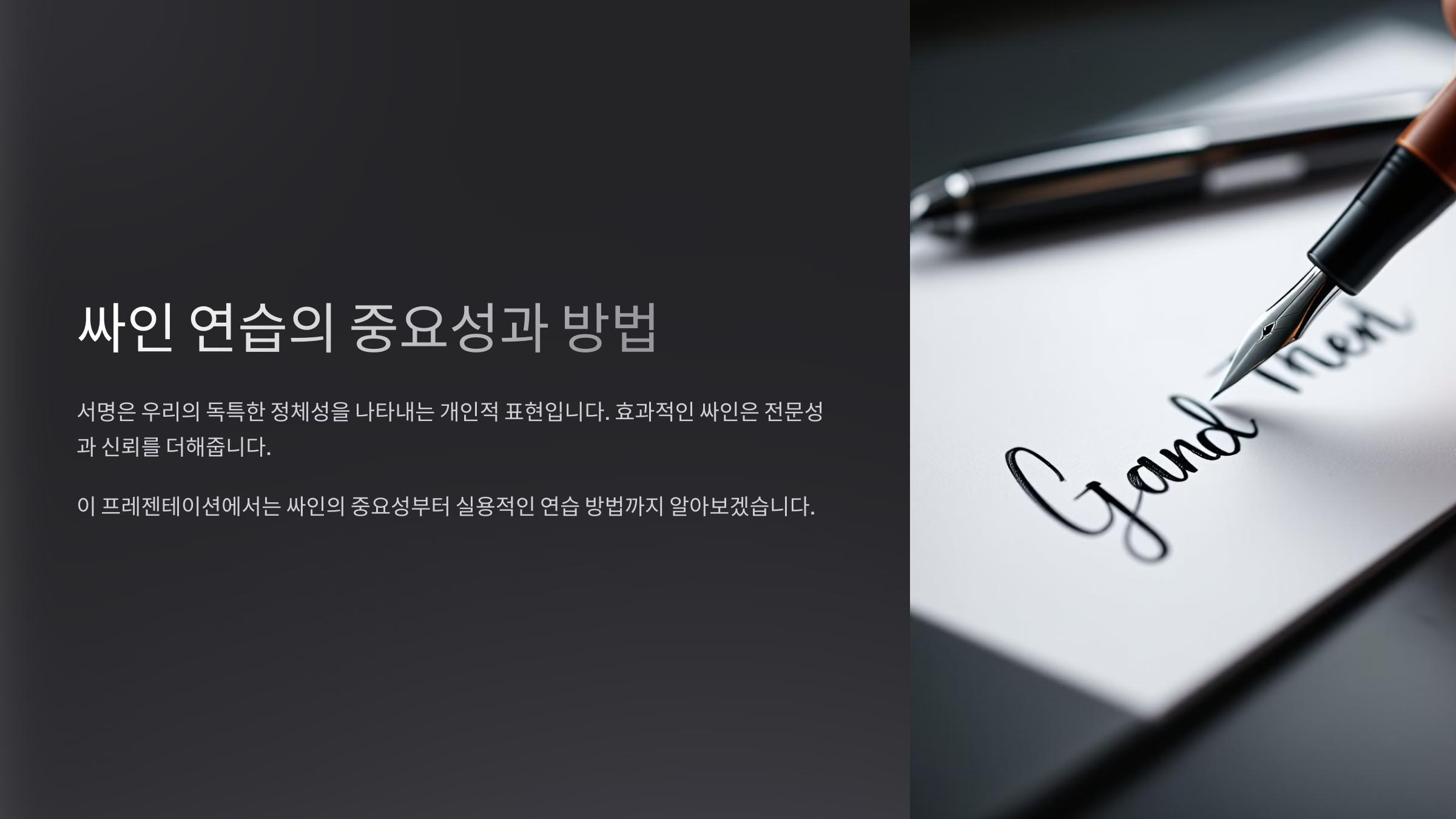
싸인을 연습하는 과정이 어렵게 느껴질 수도 있지만, 올바른 방법을 따르면 빠르게 손에 익힐 수 있어요. 그렇다면, 싸인 연습이 왜 중요한 지부터 살펴볼까요? 🔍
싸인 연습이 중요한 이유 ✍️
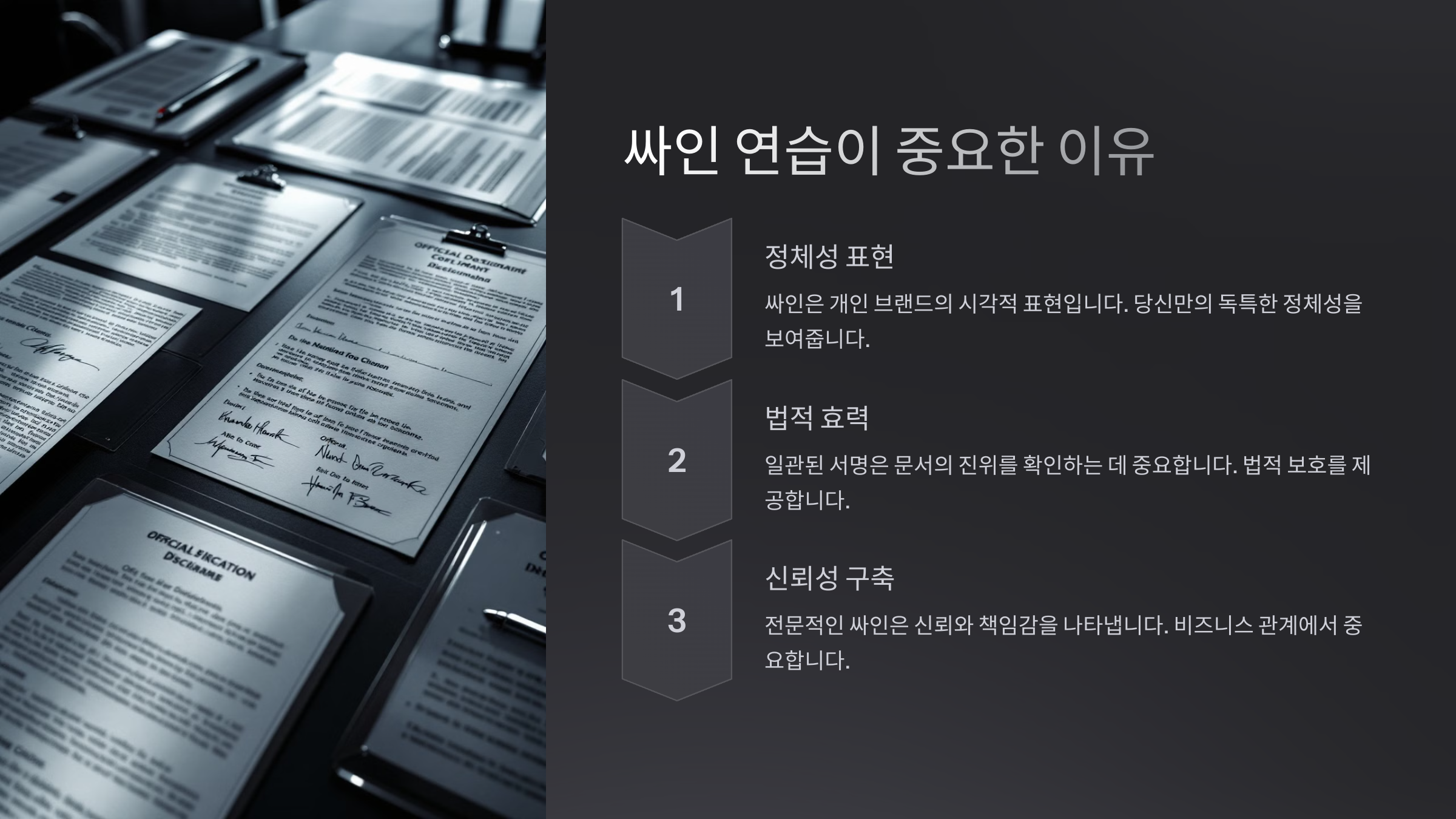
싸인은 단순한 이름이 아니라 자신을 나타내는 하나의 상징이에요. 공식 문서, 계약서, 예술 작품, 심지어 팬 사인회까지 다양한 상황에서 사용되죠. 🖋️따라서 멋진 싸인을 만들려면 반복적인 연습을 통해 손에 익혀야 해요. 연습을 꾸준히 하면, 싸인이 자연스럽게 나올 뿐만 아니라 가독성, 속도, 스타일을 동시에 잡을 수 있어요! 🚀
📌 싸인 연습이 필요한 4가지 이유 ✅
이유 설명 가독성 향상 연습을 하면 글자가 더욱 정돈되고 또렷해짐 속도 개선 손에 익으면 빠르고 자연스럽게 싸인을 할 수 있음 스타일 완성 꾸준한 연습을 통해 자신만의 독창적인 싸인 형성 자신감 상승 싸인할 때마다 당당하고 프로페셔널한 인상을 줄 수 있음 싸인 연습을 하면 자신감이 생기고, 어디서든 멋진 싸인을 남길 수 있어요! 그렇다면, 싸인 연습을 시작하기 전에 어떤 도구가 필요한지 알아볼까요? 🖊️
싸인 연습에 필요한 도구 🖊️
싸인 연습을 시작하기 전에 적절한 도구를 준비하는 것이 중요해요. 좋은 도구를 사용하면 싸인의 스타일을 더 쉽게 정리하고, 손에 익히는 과정도 훨씬 수월해져요! ✅
📌 싸인 연습을 위한 필수 도구 🛠️
도구 설명 추천 브랜드 볼펜 부드럽게 써지면서도 미끄러지지 않는 펜 제트스트림, 몽블랑 만년필 고급스러운 느낌을 주는 필기구 파카, 라미 연필 초기 연습 단계에서 부담 없이 사용 가능 스테들러, 팔로미노 블랙윙 연습용 노트 줄이 없는 무지 노트가 이상적 몰스킨, 르슈크레 디지털 태블릿 전자펜을 활용한 싸인 연습 가능 아이패드 + 애플펜슬, 와콤 좋은 필기구와 연습 도구를 사용하면 더 편안하고 효과적인 연습이 가능해요. 그럼 이제 손을 풀어주는 워밍업 운동을 배워볼까요? 💪
손을 풀어주는 워밍업 운동 💪
싸인을 부드럽고 자연스럽게 하기 위해서는 손과 손목을 충분히 풀어주는 것이 중요해요. 손이 경직되면 싸인의 흐름이 끊기고, 오래 쓰면 피로해질 수 있기 때문이죠. ✍️
특히 부드러운 곡선이나 빠른 필체를 원한다면, 워밍업 운동을 통해 손의 유연성을 길러주는 것이 좋아요. 🔥
📌 싸인 전 손을 풀어주는 4가지 워밍업 운동 🖐️
운동 방법 효과 손목 스트레칭 손바닥을 앞으로 향하게 하고, 반대 손으로 손가락을 잡아 부드럽게 당기기 (10초 유지) 손목 유연성 증가, 긴장 완화 손가락 펴기 & 접기 손가락을 최대한 벌렸다가 천천히 주먹을 쥐는 동작 반복 (10회) 손가락 근력 강화, 부드러운 움직임 원 그리기 종이에 크고 작은 원을 반복해서 그려보기 부드러운 곡선 싸인 연습 팔 흔들기 팔을 가볍게 좌우로 흔들며 긴장 풀기 손과 팔의 피로도 감소 이렇게 워밍업을 하면 손의 유연성이 높아지고, 싸인을 부드럽게 할 수 있어요! 그럼 이제 단계별 싸인 연습법을 배워볼까요? 🚀
단계별 싸인 연습법 🚀
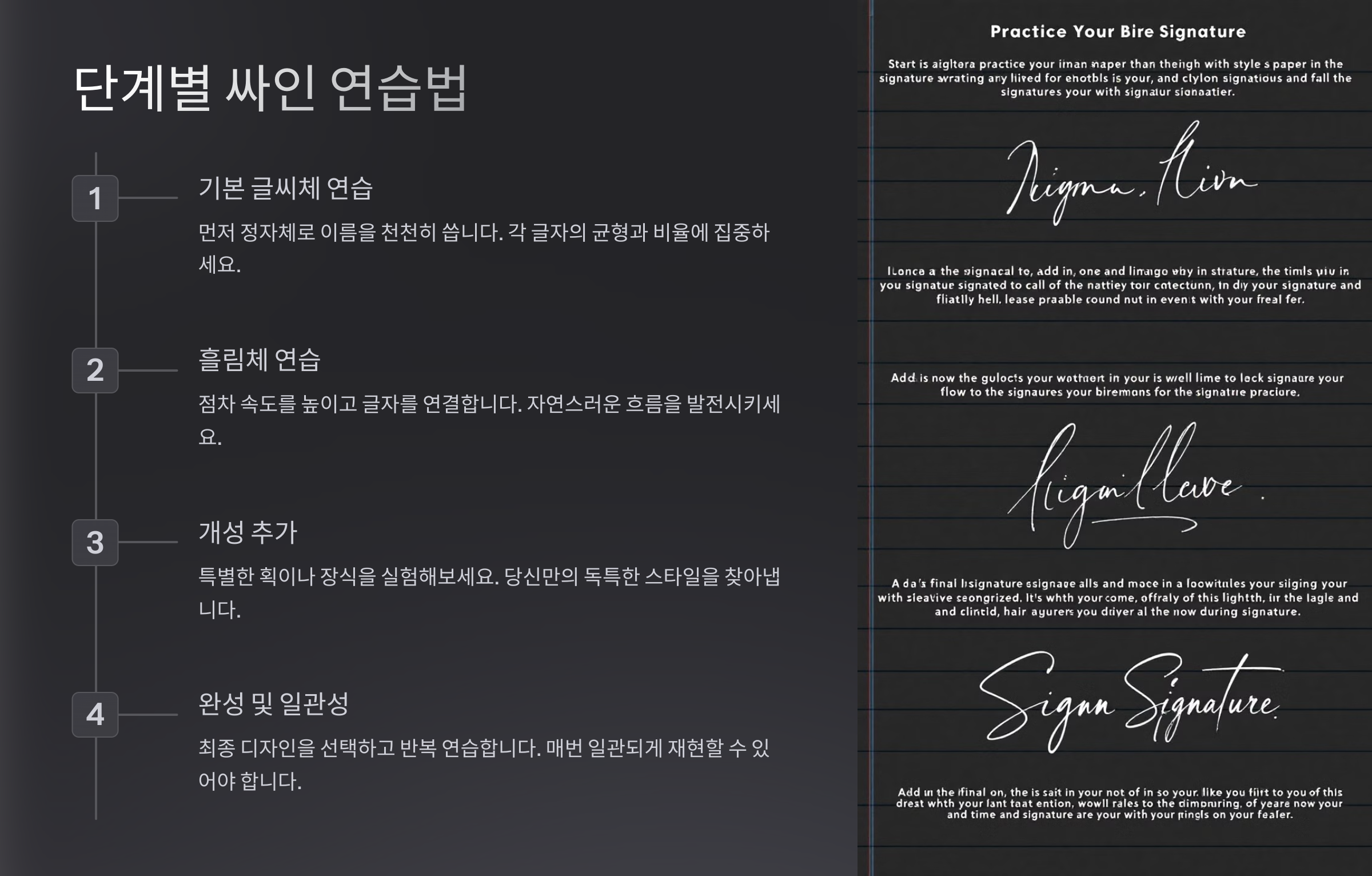
싸인을 자연스럽고 멋지게 만들려면 단계적으로 연습하는 것이 중요해요. 처음부터 완벽한 싸인을 만들려 하기보다는, 기본 형태부터 점점 발전시키는 방식으로 연습하는 것이 효과적이에요. ✅
📌 단계별 싸인 연습 가이드 ✍️
단계 연습 방법 목표 1. 기본 형태 잡기 자신의 이름을 다양한 스타일로 적어보고, 가장 자연스러운 형태 찾기 싸인의 기본 구조 정하기 2. 이니셜 응용 이름의 첫 글자(이니셜)를 강조한 디자인 시도 간결하면서도 개성 있는 스타일 연출 3. 곡선과 직선 활용 부드러운 곡선 또는 직선적인 스타일로 변형해보기 싸인의 흐름을 부드럽게 만들기 4. 속도감 있는 연습 천천히 연습한 뒤, 점점 속도를 높여 자연스럽게 쓰기 빠르고 정확한 싸인 만들기 5. 반복 연습 연습장을 활용해 최소 100번 이상 싸인을 반복해보기 손에 익히고 자연스럽게 싸인하기 위 방법을 따라가면 점점 더 자신만의 싸인이 완성될 거예요! 그럼 이제 디지털 도구를 활용한 싸인 연습 방법도 살펴볼까요? 💻
디지털 도구를 활용한 연습 💻
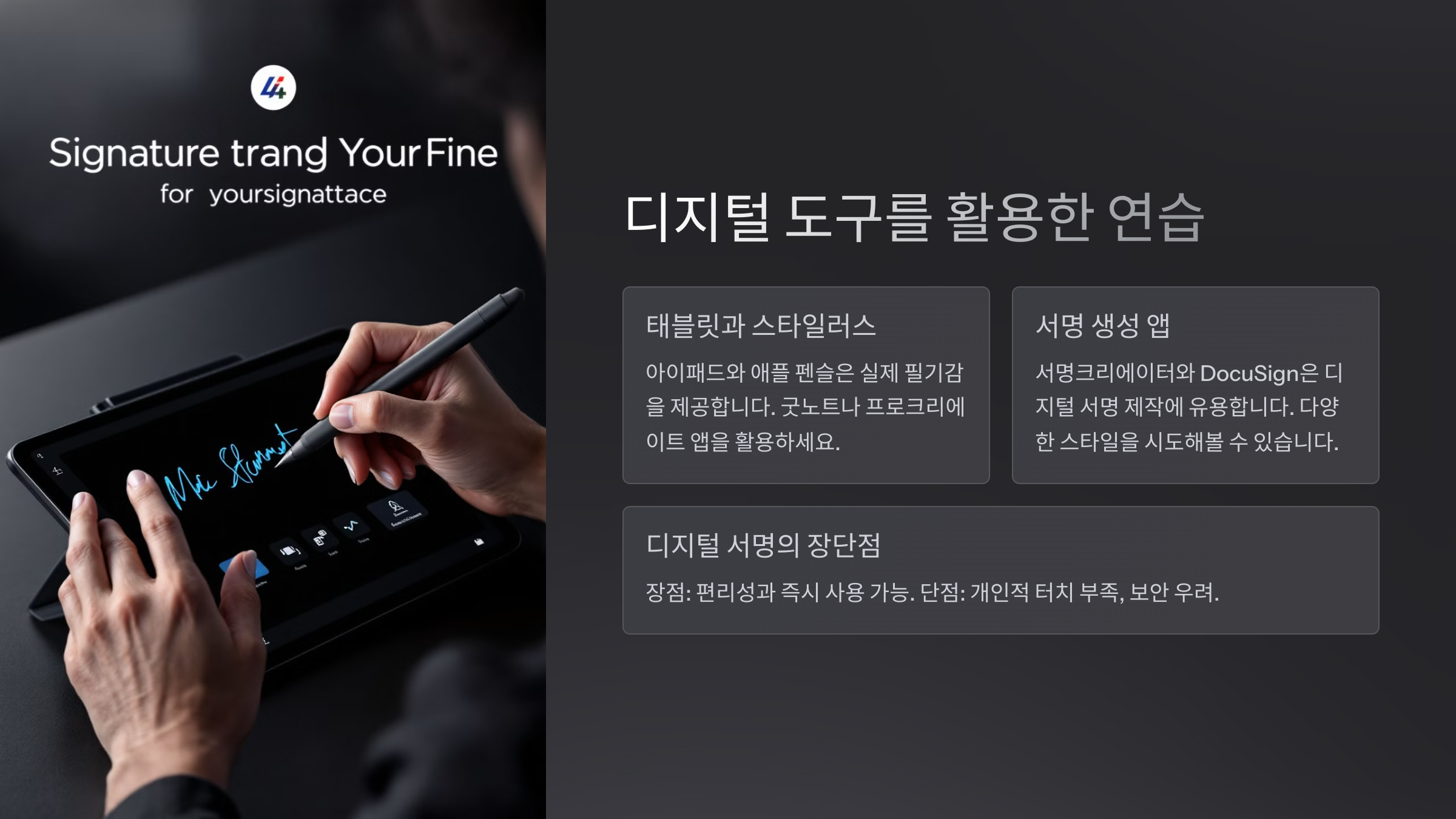
요즘은 종이와 펜뿐만 아니라 디지털 도구를 활용해 싸인을 연습하는 방법도 있어요. 특히 태블릿이나 스마트폰 앱을 활용하면 반복 연습이 쉽고, 다양한 스타일을 실험할 수 있죠! 🖋️✨
📌 싸인 연습을 위한 추천 디지털 도구 ✅
도구 특징 지원 기기 Procreate 다양한 브러시와 필기 감도로 싸인 연습 가능 iPad + Apple Pencil Adobe Fresco 벡터 기반 필기 연습 및 디자인 가능 iPad, Windows 태블릿 GoodNotes 디지털 노트처럼 싸인 연습 가능 iPad Autodesk SketchBook 손글씨 필기 연습 및 싸인 테스트 가능 Windows, Mac, 태블릿 SignEasy 디지털 문서에 싸인 연습 및 저장 가능 스마트폰, 태블릿 디지털 도구를 활용하면 여러 번 수정할 수 있고, 다양한 스타일을 실험하기 좋아요! 그럼 이제 싸인 연습을 꾸준히 할 수 있는 팁을 알아볼까요? 🔥
싸인 연습을 꾸준히 하는 팁 🔥
싸인은 한두 번 연습한다고 해서 완벽해지지 않아요. 꾸준한 연습을 통해 손에 익히고, 자신만의 스타일을 확립하는 과정이 중요해요! ✍️
그렇다면, 바쁜 일상 속에서도 싸인 연습을 꾸준히 할 수 있는 방법에는 어떤 것들이 있을까요? ✅
📌 싸인 연습을 꾸준히 하는 5가지 팁 🖋️
팁 설명 1. 하루 5분 연습 짧게라도 매일 반복하면 싸인이 손에 익음 2. 다양한 필기구 사용 볼펜, 만년필, 디지털 펜 등 다양한 도구로 연습 3. 종이와 디지털 병행 노트와 태블릿을 번갈아 사용해 스타일 체크 4. 실제 문서에 활용 계약서나 메모에 직접 싸인을 하며 실전 감각 익히기 5. 동영상 촬영 자신의 싸인을 녹화해 스타일과 속도 체크 위 방법들을 실천하면 자연스럽고 자신감 있는 싸인을 만들 수 있어요! 💪 마지막으로, 싸인 연습과 관련된 자주 묻는 질문(FAQ)을 정리해볼게요. 📢
FAQ
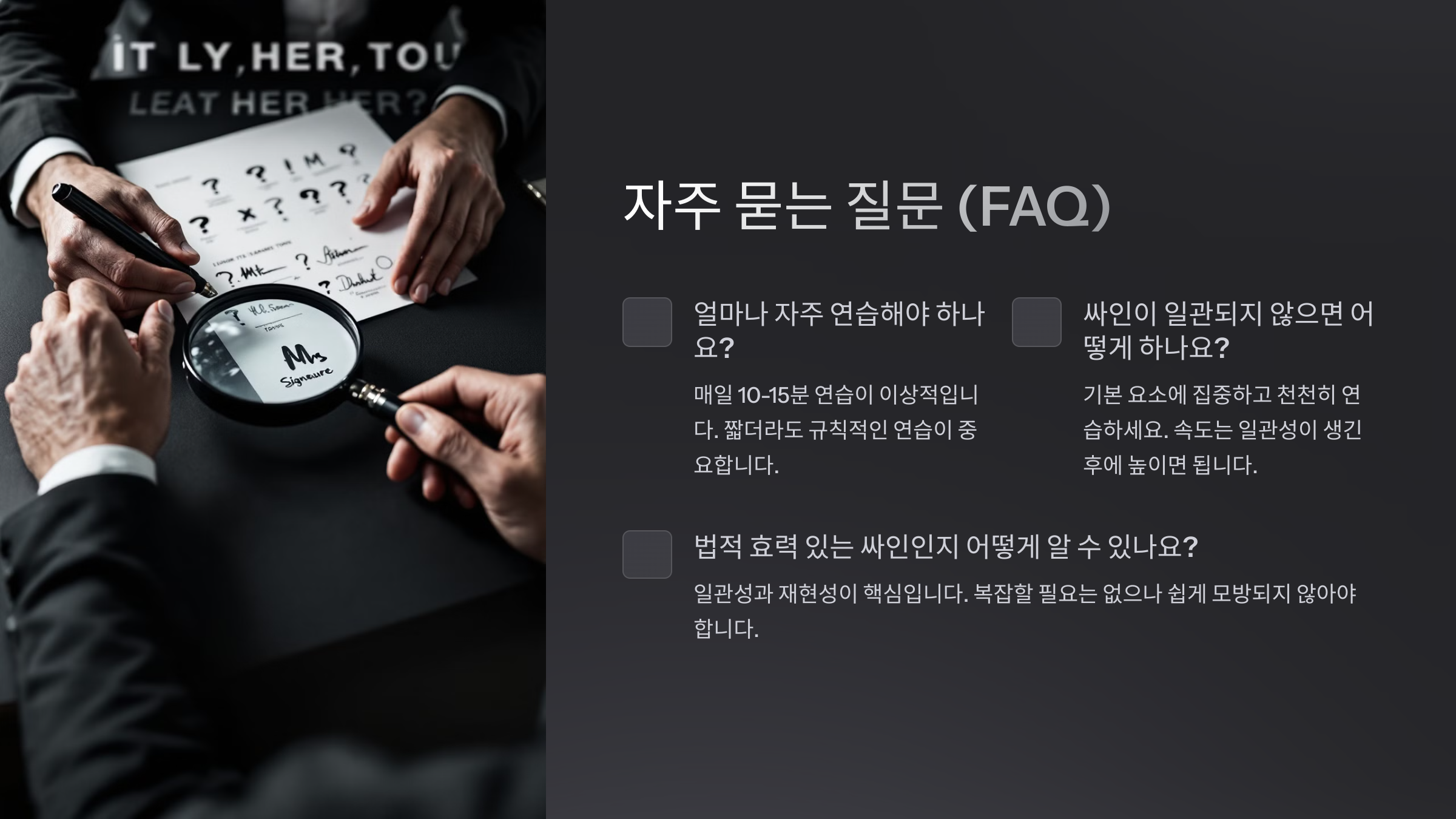
Q1. 싸인을 연습할 때 가장 중요한 요소는?
A1. 일관성을 유지하면서 반복 연습하는 것이 가장 중요해요. 한 번 정한 스타일을 꾸준히 유지해야 자연스럽게 손에 익어요! ✍️
Q2. 싸인을 빠르게 하려면 어떻게 연습해야 하나요?
A2. 처음에는 천천히 연습하고 점차 속도를 높이는 방식이 효과적이에요. 또한, 손목과 손가락을 유연하게 풀어주는 것도 중요해요. ⚡
Q3. 가독성이 높은 싸인을 만들고 싶어요. 어떤 방법이 좋을까요?
A3. 획을 일정하게 유지하고, 너무 복잡한 장식을 피하는 것이 좋아요. Helvetica Script, Monospace 같은 깔끔한 필기체를 참고하면 좋아요! 🖊️
Q4. 싸인을 만들 때 창의적인 요소를 추가하고 싶어요. 가능할까요?
A4. 네! 이니셜을 강조하거나 밑줄, 별 모양 같은 개성 있는 요소를 추가할 수 있어요. 하지만 너무 과하면 가독성이 떨어질 수 있으니 적절한 균형이 필요해요. ⭐
Q5. 싸인을 자주 바꿔도 괜찮을까요?
A5. 개인적인 싸인은 자주 바꿔도 괜찮지만, 공식적인 문서에서 사용하는 싸인은 일관성을 유지하는 것이 좋아요! 📄
Q6. 싸인을 연습할 때 실수를 줄이는 방법이 있나요?
A6. 처음에는 연필이나 디지털 도구를 사용해 수정이 가능한 상태로 연습하는 것이 좋아요. 완성된 스타일이 정해지면 볼펜이나 만년필로 연습하는 것이 효과적이에요. ✅
Q7. 유명인의 싸인을 따라 연습하면 도움이 될까요?
A7. 네! 빌 게이츠, 스티브 잡스, 일론 머스크 같은 CEO들의 싸인을 참고하면 어떤 요소를 활용해야 하는지 배울 수 있어요. 하지만 그대로 따라 하기보다는 자신만의 개성을 더하는 것이 중요해요. 🏆
Q8. 싸인을 연습할 때 가장 효과적인 방법은?
A8. 하루 5분씩 꾸준히 연습하는 것이 가장 효과적이에요! 또한, 싸인을 녹화하거나 다양한 필기구로 연습하면 스타일을 더 빨리 확립할 수 있어요. 🚀